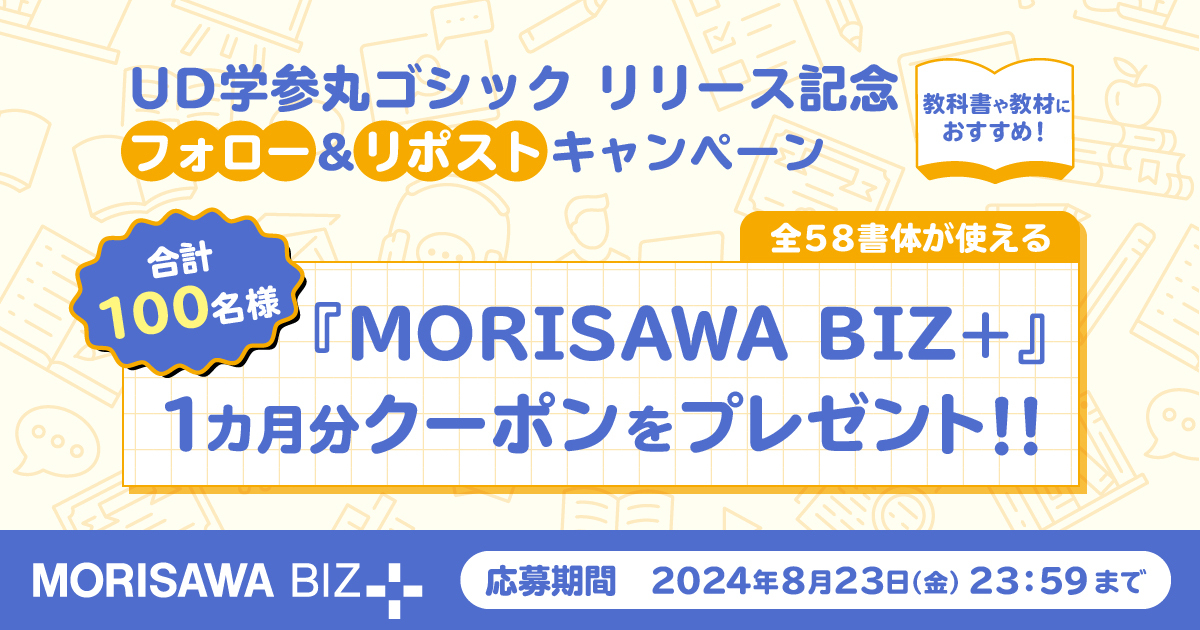
モリサワ 本日よりMORISAWA BIZ+で「UD学参丸ゴシック」を提供開始、リリースを記念してUDフォントのクーポンが100名様に当たるSNSキャンペーンを実施
株式会社モリサワ(代表取締役社長:森澤彰彦 本社:大阪市浪速区敷津東2-6-25 Tel:06-6649-2151 代表、以下モリサワ)は、本日より、モリサワのUDフォントが使えるサービス「MORISAWA BIZ+」および「MORISAWA BIZ+ 公共団体向けUDフォントプラン」を通じて、教科書・教材のために開発された丸ゴシック体「UD学参丸ゴシック」の提供を開始しました(※)。これを記念し、モリサワ公式X(旧Twitter)では「MORISAWA BIZ+」の電子クーポン1ヶ月分を抽選で100名様にプレゼントするフォロー&リポストキャンペーンを実施します。
「UD学参丸ゴシック」は、読み書きに困難さのある児童・生徒を含む多くの子どもたちの学習を支援する書体です。全ての和文の文字が文部科学省の学習指導要領の字形に準拠(学参化)しているほか、英数字の形をわかりやすくしており、子どもたちの発達段階や使用目的などに合わせて、「BIZ UDゴシック」「UDデジタル教科書体」など他のUDフォントと併用したり、使い分けたりすることが可能です。
モリサワのUDフォントについて
「文字のかたちがわかりやすいこと」「文章が読みやすいこと」「読み間違えにくいこと」をコンセプトに開発されています。具体的には、濁点、半濁点を大きくして、区別をつけやすくしているほか、シルエットの似た文字を判別しやすくするために、はなれを明確にするなどの工夫がされています。また、第三者機関と共同で可視性・可読性に関する比較研究報告も実施しています。